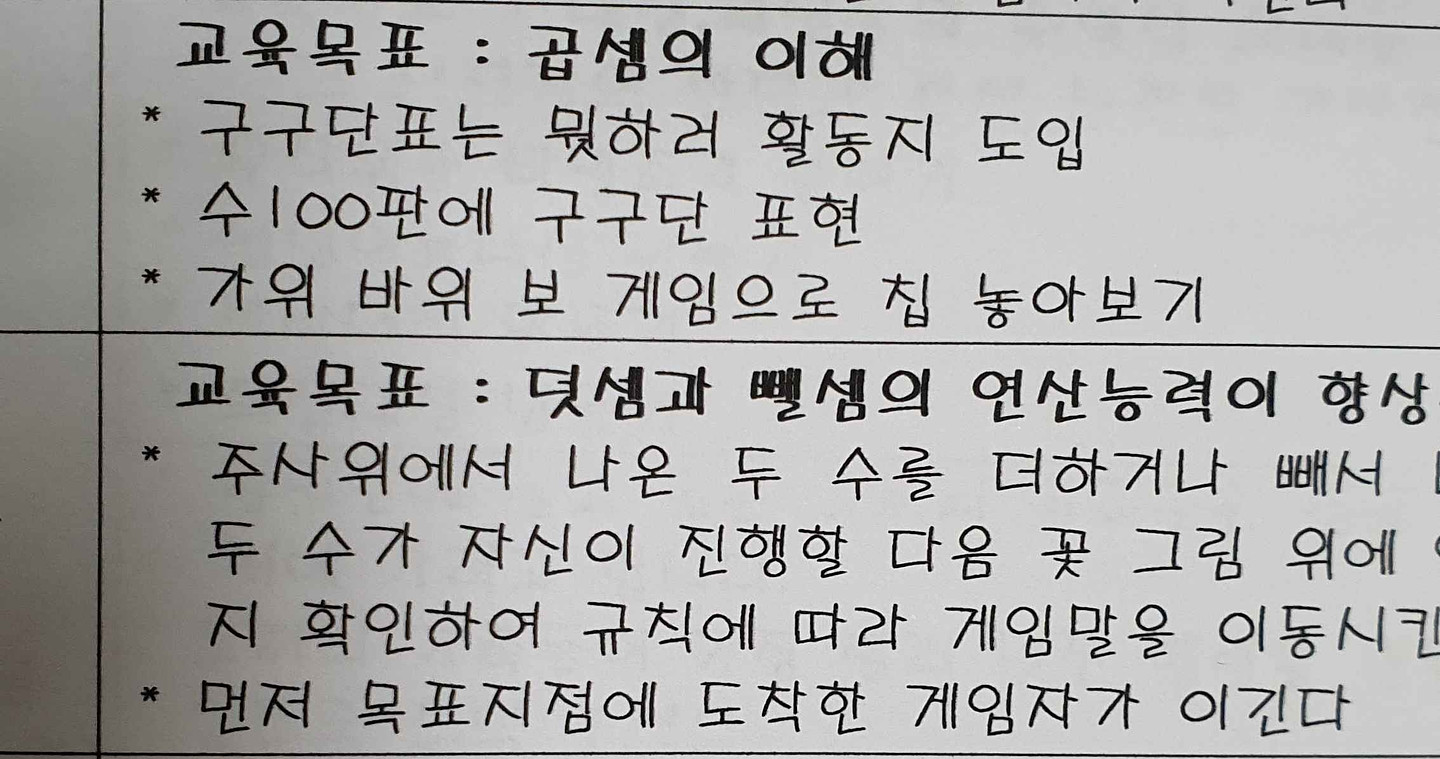
ㅏㅑㅓㅕ 계열의 세로형 모음이 있는 글자의 초성에 ㄱ이 올 경우 특유의 생김새가 있는 필기체 형태의 글씨체입니다. 2011년쯤에 쓰여진 것으로 추정되는 문서의 일부입니다. 개인적인 생각으로는 한글 프로그램의 기본 서체가 아닌가 하여 찾아보았으나 찾지 못했습니다. 찾아주시는 분께는 정말 감사드립니다.